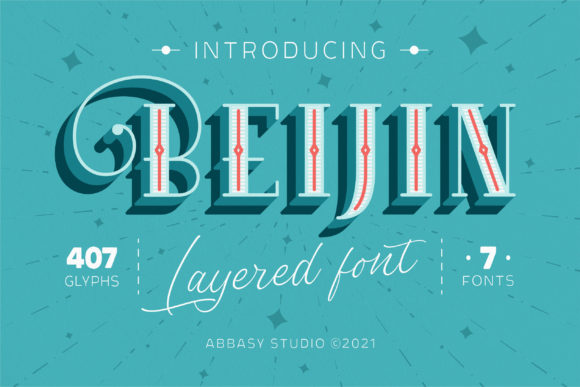
Creativefabrica Beijin Font
[Creativefabrica] Beijin Font
Пекин - это уникальный и интересный шрифт для отображения на дисплее.
Немного причудливый, этот шрифт - отличный выбор для самых разных контекстов!